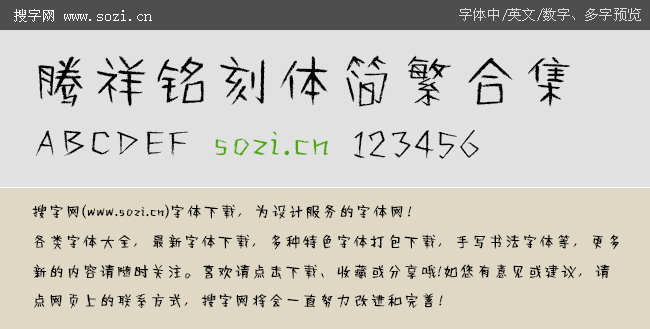
騰祥銘刻體簡繁合集
搜字網(wǎng)提供一款騰祥銘刻體簡繁合集中文藝術(shù)字體下載,騰祥銘刻體是一款很好看的字體,筆畫詭直,像是用小刀刻上去的一樣,非常有藝術(shù)效果,字體可以廣泛應(yīng)用于橫幅標(biāo)語、美術(shù)設(shè)計(jì)、宣傳海報(bào)、圖形設(shè)計(jì)等領(lǐng)域。